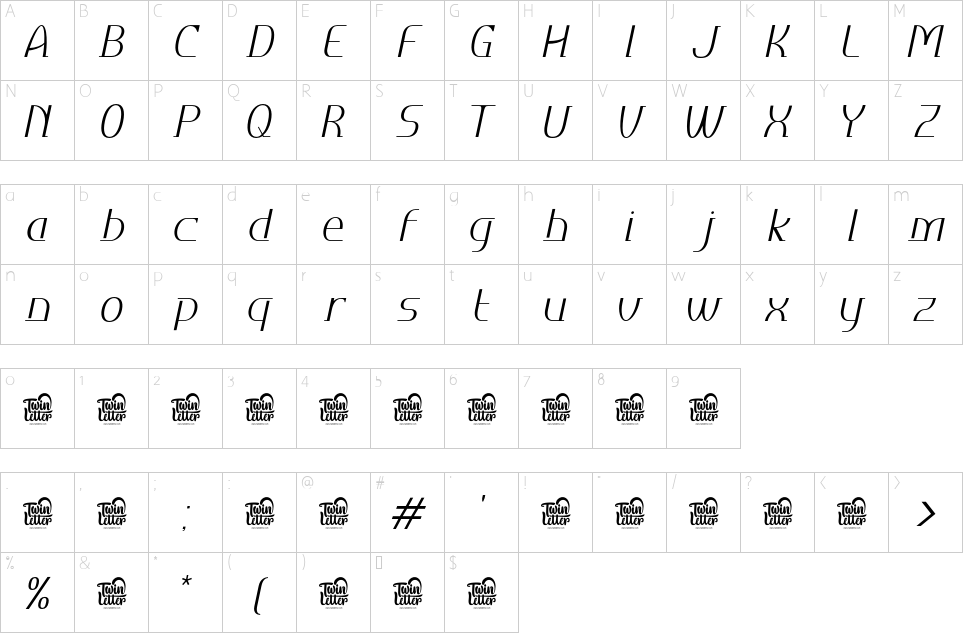
Daimor Font – Download Grátis
A Daimor é uma elegante fonte que combina sutileza com modernidade. Ela foi criada pelo designer rozi e já tem mais de quatro mil downloads, demonstrando sua popularidade entre designers e criadores de conteúdo digitais. Esta fonte é perfeita para usar em projetos pessoais ou profissionais, oferecendo uma aparência atraente sem comprometer o conforto do leitor. Se você está procurando por uma solução moderna e elegante que não seja carregada demais, Daimor pode ser seu próximo escolha de fonte.